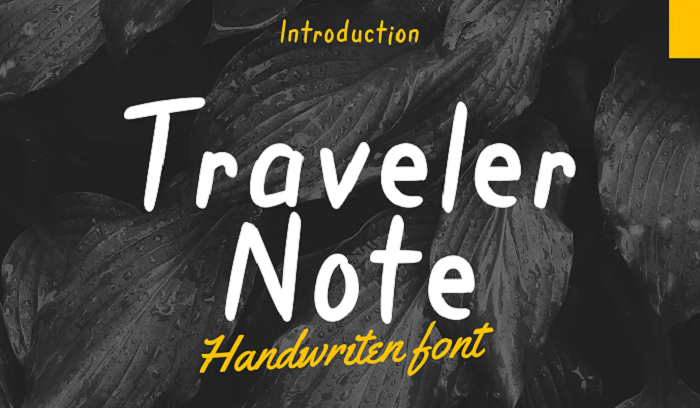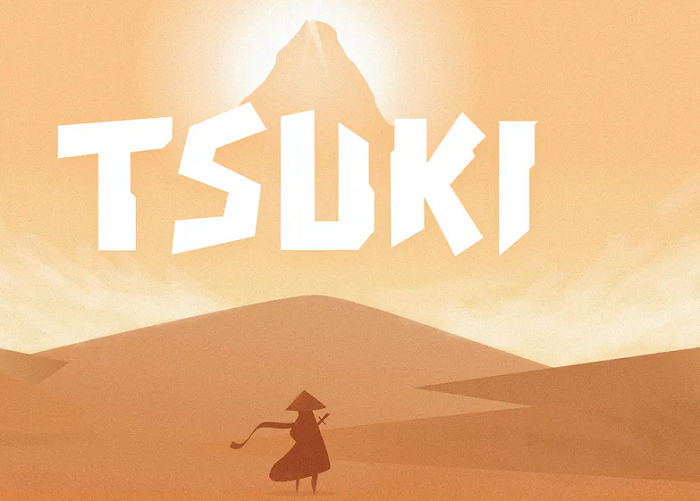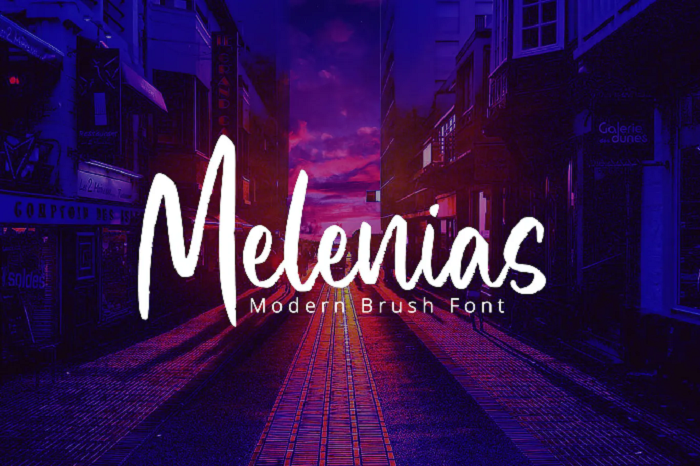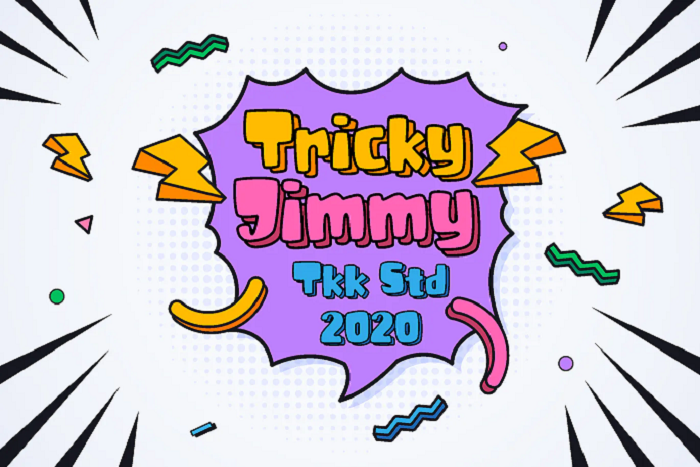
Najlepsza czcionka Youtube na rok 2023
Wybierając czcionkę YouTube, należy zadać sobie 4 pytania:
- Czy czcionka jest stylowa?
- Czy przyciąga twoją uwagę?
- Czy łatwo się to czyta?
- A co najważniejsze — czy klikniesz?
Nasz najlepszy wybór spełnia wszystkie te kryteria, rzućmy na to okiem.
1. Dustin Font Quartet — wszechstronna rodzina czcionek YouTube — nasz najlepszy wybór
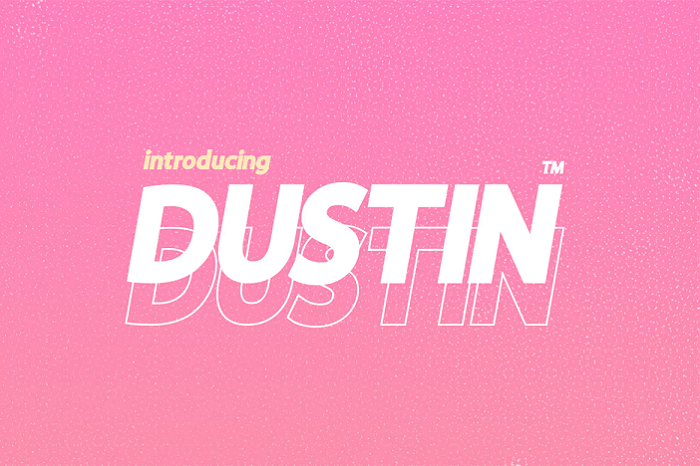
Rodzina czcionek Dustin to świetny wybór dla YouTuberów. To wszechstronny pakiet czterech uzupełniających się czcionek. W zestawie znajduje się zwykła czcionka, zwykła czcionka konturowa i kursywa w obu wersjach.
Czcionka przypomina supermodne logo marek, takich jak Supreme i z pewnością przyciągnie uwagę widzów.
Dlaczego jest to nasz najlepszy wybór
Jest nowoczesny, stylowy i minimalistyczny, dzięki czemu idealnie nadaje się do każdego rodzaju filmów na YouTube. Jest łatwy do odczytania, więc można go używać w filmach i miniaturach. I jest odważny, więc naprawdę wyskakuje ze strony.
Najlepsze czcionki do miniatur YouTube
Wszystkie poniższe czcionki są idealne do tworzenia przyciągających wzrok miniatur, które można łatwo kliknąć.
2. Krój pisma Traveler — czcionka YouTube dla kanałów Adventure and Travel
Krój pisma Traveler przypomina czcionki używane przez popularnych YouTuberów, takich jak Sam Kolder i inni podróżnicy YouTube.
Stylowe litery pędzla są wyraźne i odważne, dzięki czemu idealnie nadają się zarówno do miniatur, jak i grafik kanałów.
3. Caribold – pogrubiona czcionka dla miniatur YouTube
Caribold to znakomita czcionka, która doskonale nadaje się do różnych filmów na YouTube. Czcionka jest bardzo efektowna i naprawdę się wyróżnia, dzięki czemu jest wysoce klikalną czcionką miniatur.
4. Herona – czcionka YouTube dla kanałów z grami
Herona to jedna z najlepszych czcionek YouTube dla kanałów o grach. Projekt jest retro i jest inspirowany trendami w grach i e-sporcie.
Jest odważny i efektowny i świetnie wygląda w połączeniu z konturem lub cieniem.
5. Jeźdźcy — kreatywna czcionka do miniatur YouTube
Horsemen to superfajna czcionka w stylu retro. Czcionka jest inspirowana muzyką i grafiką z lat 70. i świetnie wygląda w miniaturach, grafikach kanałów i tytułach filmów. Pakiet czcionek zawiera ukośną i prostą wersję czcionki.
6. Quantum Profit – odważna i zabawna czcionka YouTube
Quantum Profit to zabawna i zakrzywiona czcionka zaprojektowana z myślą o dzieciach.
Niezależnie od tego, czy tworzysz recenzje zabawek, czy filmy edukacyjne, ta czcionka YouTube z pewnością przyciągnie wzrok maluchów przeglądających YouTube dla dzieci.
7. Chucklesome — Czcionka miniatury w stylu kreskówki
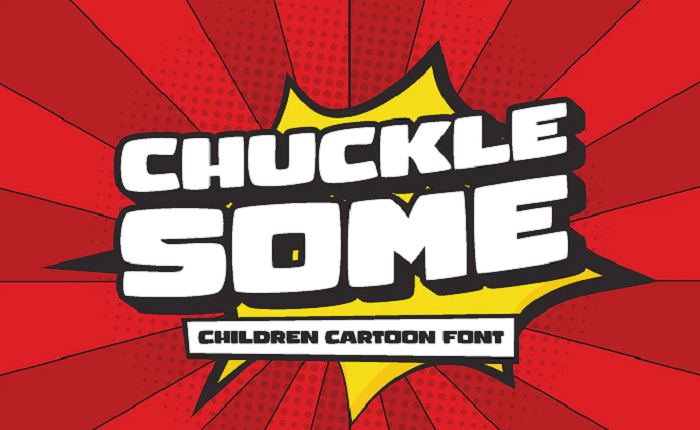
Chucklesome to odważna i dziwaczna czcionka rysunkowa inspirowana komiksami. Gruba i efektowna czcionka naprawdę wyróżnia się, gdy jest używana w miniaturach, i świetnie wygląda w filmach i na banerach kanałów.
8. Wolfskin — Czcionka miniatury Urban Block YouTube
Wolfskin to efektowna czcionka blokowa o miejskim charakterze. Ta czcionka jest świetna dla kanałów, które chcą stworzyć agresywną estetykę, takich jak kanały parkour lub uliczne. W przypadku miniatur ta czcionka wygląda świetnie w połączeniu z grubym konturem lub cieniem.
9. The Tide – Czcionka blokowa dla kanałów Lifestyle
The Tide to odważna i modna czcionka, dzięki której poczujesz się jak na plaży w Kalifornii. Czcionka jest ładna i gruba, więc świetnie nadaje się do tworzenia wyróżniających się miniatur. The Tide to świetna opcja dla zrelaksowanych vlogerów zajmujących się stylem życia i filmów #vanlife.
10. Frisky Puppy – przyjazna dzieciom czcionka YouTube
Frisky Puppy to kolejna super urocza czcionka, która jest idealna dla kanałów skierowanych do dzieci. Odważny, kreskówkowy projekt naprawdę sprawia, że miniatury wyskakują, a dzieci są niezwykle łatwe do odczytania.
11. Wandalizm – Czcionka pędzla dla kanałów przygodowych
Vandalism to stylowa miejska czcionka, która doskonale nadaje się do kanałów przygodowych i vlogów podróżniczych. Czcionka jest łatwa do odczytania, a odręczny styl sprawia, że miniatury wyglądają naprawdę fajnie i niepowtarzalnie.